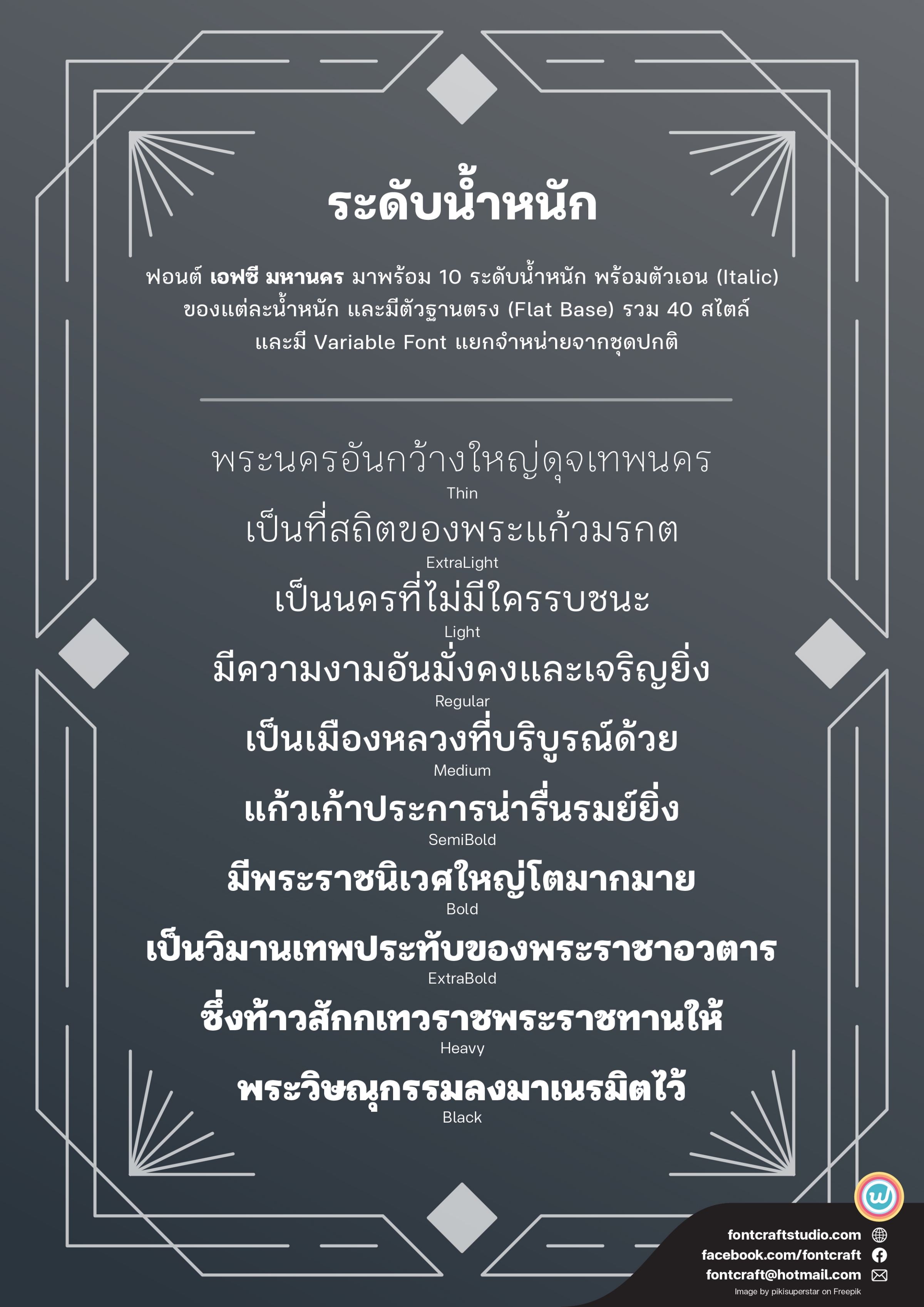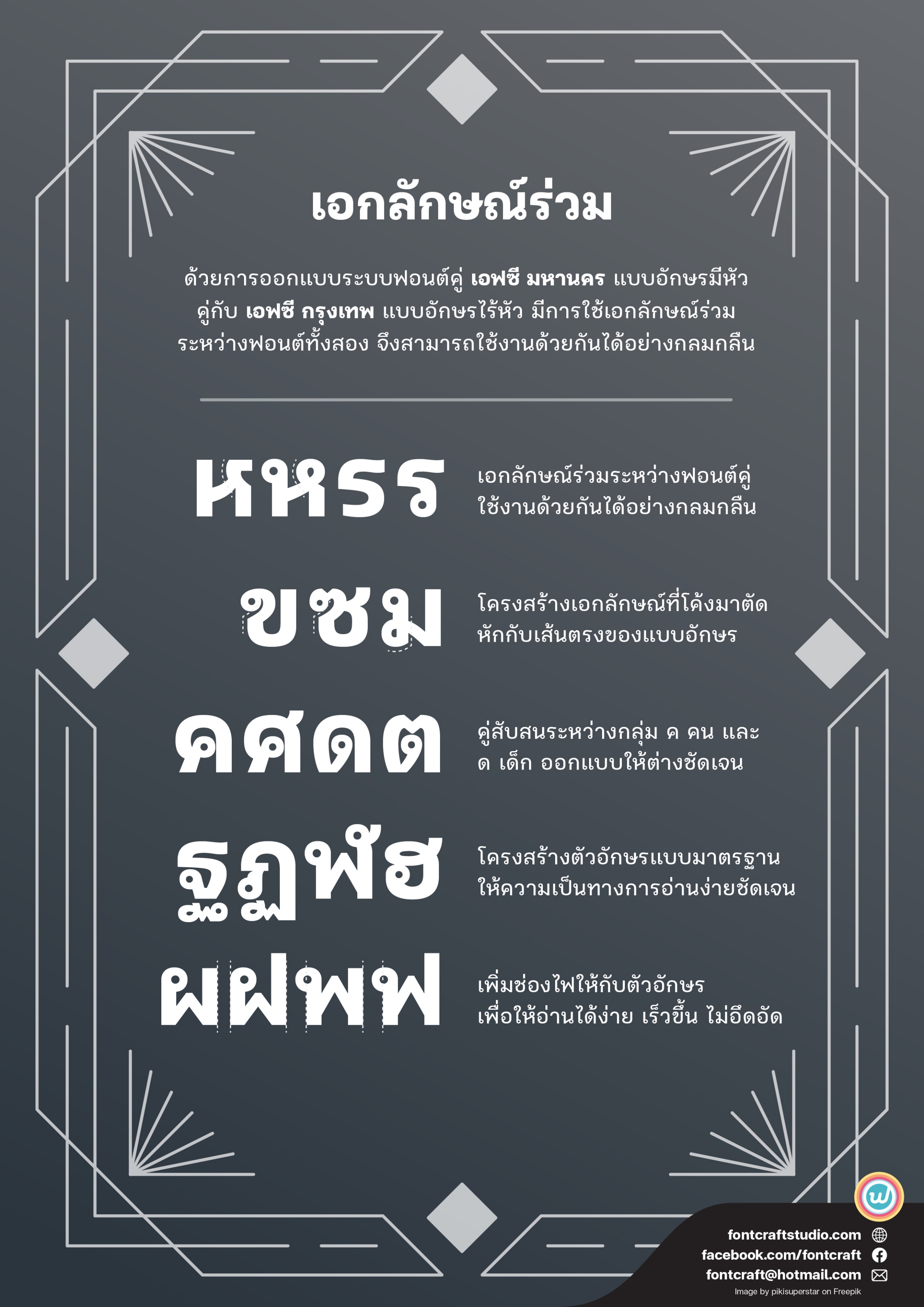
เอฟซี มหานคร (FC Maha Nakhon)
ฟอนต์เอฟซี มหานคร (FC Maha Nakhon)
ฟอนต์ไทยมีหัวกลมที่อ่านง่ายชัดเจน ทางการอย่างไทย
สะท้อนบุคลิกของความเป็นมหานครเมืองหลวง
ฟอนต์เอฟซี มหานคร เป็นฟอนต์ไทยแบบมีหัว
ด้วยเอกลักษณ์เฉพาะตัวผ่านส่วนโค้งและตัดหัก อันเป็นจุดสังเกตที่จดจำได้ง่าย
เหมาะสำหรับการใช้ในส่วนของตัวเนื้อความที่ต้องการให้อ่านได้ง่ายและเร็ว
และอ่านได้เร็วขึ้นเมื่อเลือกใช้แบบฐานตรง (Flat Base)
ออกแบบคู่กับฟอนต์ กรุงเทพ (FC Krung Thep) ที่เป็นฟอนต์ไทยแบบไร้หัว
มีการใช้เอกลักษณ์ร่วมระหว่างฟอนต์ทั้งสอง จึงสามารถใช้งานด้วยกันได้อย่างกลมกลืน
มาพร้อมกับ 10 ระดับน้ำหนักและตัวเอน รวม 40 สไตล์
ฟอนต์ชุดนี้รองรับการปรับแต่งน้ำหนักและความกว้างโดยละเอียด (Variable Font) จำหน่ายแยกจากฟอนต์ชุดหลัก